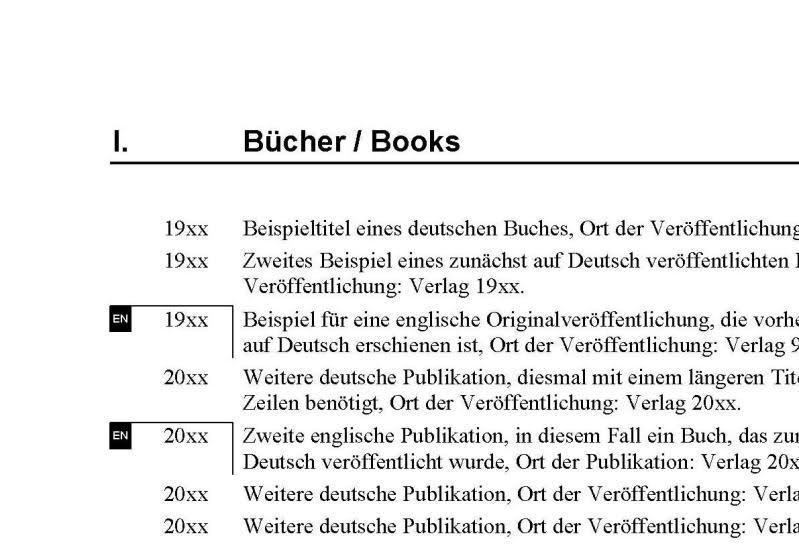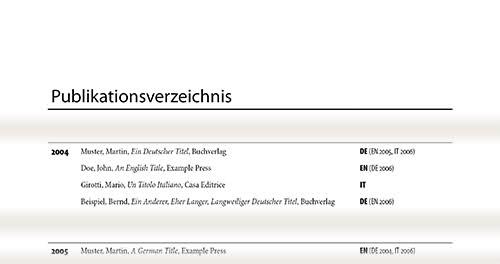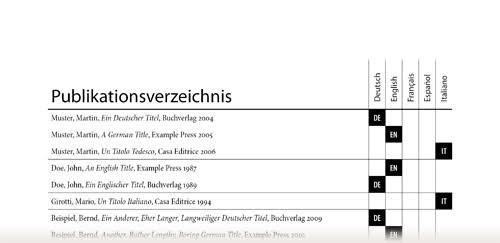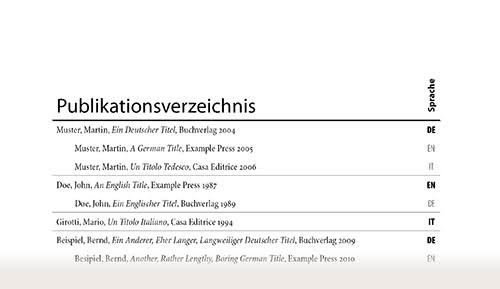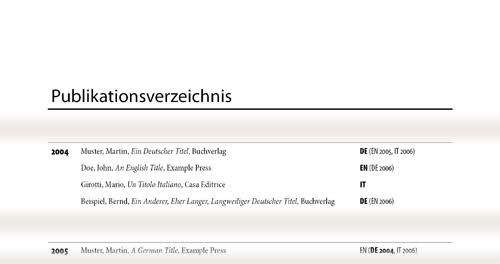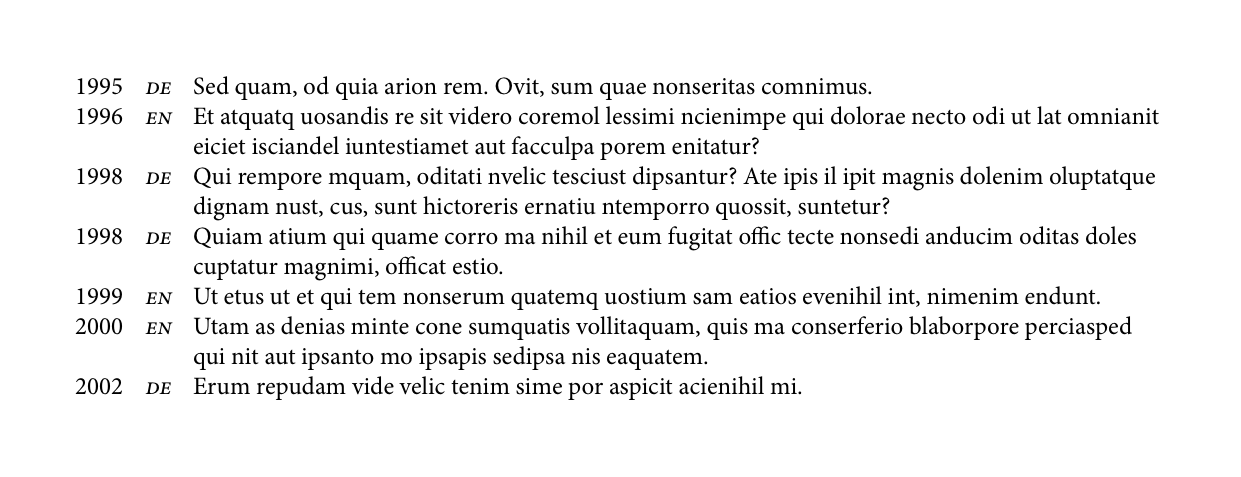
Publikationsverzeichnis
Ja, ich find auch dass man da nicht mehr erkennen kann, was was sein soll ... Oder ich hab das Problem nicht verstanden :D
Wie wär es denn so – ohne Anspruch auf Schönheit, mal für den Papierkorb ...? ;)
Leider habt ihr Recht. Ich habe noch weitere "Strich"-Varianten probiert, die aber auch nicht wirklich überzeugen. Zum Beispiel so:
Die Variante, die einzelnen Sprachen in einer Tabelle abzuhaken, ist zwar eindeutig, aber ein wenig technisch. Immerhin wird sie den verschiedenen Sprachen gerecht, was man von meiner Version nicht behaupten kann, die ja wieder nur englische Titel hervorhebt.
Ich habe den Verdacht, dass das Verzeichnis zu viele Dinge gleichzeitig versucht: alle Publikationen auflisten; zeigen, in welche Sprachen Werke übersetzt wurden; für englische Leser quasi ein "englisches Verzeichnis" mit entsprechendem Layout bieten; forschungspragmatisch leicht benutzbar sein ("Stellen sie die Publikationen der letzten 5 Jahre für Ihre Bewerbung zusammen" – wenn dieser Aspekt nicht wäre, könnte man die Übersetzungen wunderbar unter der Originalveröffentlichung zusammenfassen und einen kleinen eleganten Sprachverweis davorsetzen; man müsste die Werke nicht alle chronologisch einsortieren).
Ich sehe schon, am Ende werde ich doch noch die Fraktur/Antiqua-Version vorschlagen ...
Ich habe den Verdacht, dass das Verzeichnis zu viele Dinge gleichzeitig versucht
Möglich. Mir kam, als ich Minimalists Variante sah, noch ein anderer Gedanke: ich bin mir nicht sicher, ob es auf breite Zustimmung treffen würde, Veröffentlichungen, die lediglich Übersetzungen bereits erwähnter Veröffentlichungen sind, als quasi selbstständige Einträge aufzuführen. Da könnte bei flüchtiger Betrachtung der Eindruck entstehen, dass der Autor doppelt so viele Beiträge zu seiner Disziplin geleistet hat als tatsächlich. (Die Übersetzungsleitsung gebührt wohl dem Übersetzer.)
Als technisch sauber fallen mir auf die Schnelle folgende Varianten ein:
1. du gibst nur den Titel der Originalversion an; dahinter dann die Codes der Übersetzungen, der Code der Originalversion vielleicht besonders ausgezeichnet. Z.B.
?Darwin, Charles. On the Origin of Species. London, 1859???EN?DE?FR
Nachteil hier: du listet nur Erscheinungsort und -jahr der unübersetzten Originalveröffentlichung.[/*:m:3kkkyv38]
2. Eine leichte Abwandlung: Mach eine Tabelle wie von Minimalist vorgeschlagen und trage statt der Sprachen-Codes das Jahr der Erstveröffentlichung in der jeweiligen Sprache ein.
?Darwin, Charles. On the Origin of Species.??????????1859?1860?1862
Im Tabellenkopf würde die jeweiligen Sprachen stehen.[/*:m:3kkkyv38]
3. Du gibst die Titel der Übersetzungen mit an. (Das ist wohl an nächsten an dem, was du bisher vorgeschlagen hast.)
?Darwin, Charles. On the Origin of Species. London, 1859?????EN
????????? Die Entstehung der Arten. Berlin, 1860?????DE
Irgendwo dann der Hinweis, dass kursive Einträge (lediglich) Übersetzungen sind.[/*:m:3kkkyv38]
2. und 3. ließen sich natürlich auch kombinieren, um die Chronologie zu verdeutlichen.
Was wolltest du ursprünglich? Wenn vorhanden, sowohl englische als auch deutsche Titel angeben (aber nicht die dritter Sprachen), aber von allen Sprachen die Codes?
Ich fände die Variante viel einfacher und platzsparender:
Ob das jetzt kursiv und in Kapitälchen sein muss ist egal. Es funktioniert jedenfalls ganz simpel mit verschachtelten Formaten und Tabulatoren.
Eine heikle Frage, wie Publikationen im Verzeichnis aufzulisten sind. In meinem Fall gibt es die explizite Vorgabe, Übersetzungen als eigene Publikation chronologisch einzusortieren – die Übersetzung erscheint also als eigenes, quasi neues Buch. Man kann trefflich darüber streiten, wie man das findet. "Mein" Autor gehört nicht einmal zur Gruppe derer, die künstlich die Publikationsliste aufbauschen müssen, weil sie eigentlich nichts substantielles geschrieben haben; die streng chronologische Variante hat vor allem pragmatische Gründe: Leider gibt es in Drittmittelanträgen u.ä. noch häufig die Vorgabe, Publikationen aus einem bestimmten Zeitraum aufzulisten – und da heißt es, je mehr, je besser. Übersetzungen zählen da genauso wie Erstveröffentlichungen; und wenn alles chronologisch einsortiert ist, kann man die Sachen einfach mit copy/paste übertragen.
Die Vorgabe, dass die Liste auch für englische Leser gut geeignet sein soll, kommt schlicht daher, dass der Autor tatsächlich häufig mit amerikanischen Unis zu tun hat. Eigentlich bräuchte es zwei getrennte Listen – aber auch das soll explizit vermieden werden. Und so müssen mehrere eigentlich nicht gut zu verbindende Ziele mit der Liste erreicht werden. ... bislang noch typografisch unzureichend.
Die Variante, die einzelnen Sprachen in einer Tabelle abzuhaken, ist zwar eindeutig, aber ein wenig technisch.
Mir kam, als ich Minimalists Variante sah, noch ein anderer Gedanke: ich bin mir nicht sicher, ob es auf breite Zustimmung treffen würde, Veröffentlichungen, die lediglich Übersetzungen bereits erwähnter Veröffentlichungen sind, als quasi selbstständige Einträge aufzuführen.
Berechtigte Einwände :D Hier nochmal eine Variante mit etwas mehr Sexappeal; aufgeräumter, klarer, weniger tabellenartig, Übersetzungen eingerückt um die Kursive für die Titel zu reservieren und trotzdem eindeutiger zu sein:
P.S.:
Ich habe den Verdacht, dass das Verzeichnis zu viele Dinge gleichzeitig versucht [...]
P.S.: Vielleicht könntest Du auch jeweils nur beim Original das Kürzel fett setzen, und dann bei den zugehörigen Übersetzungen auch das Kürzel und die Jahreszahl des Originals, aber nicht das Kürzel der Übersetzung ... Ist zwar klar, dass das Original das mit dem frühesten Erscheinungsjahr sein muss, aber ist vielleicht ganz nützlich, diese Info ebenfalls auf den ersten Blick zu haben ... :? Bin jetzt aber grad zu faul, das jetzt nochmal umzubasteln ... ;)